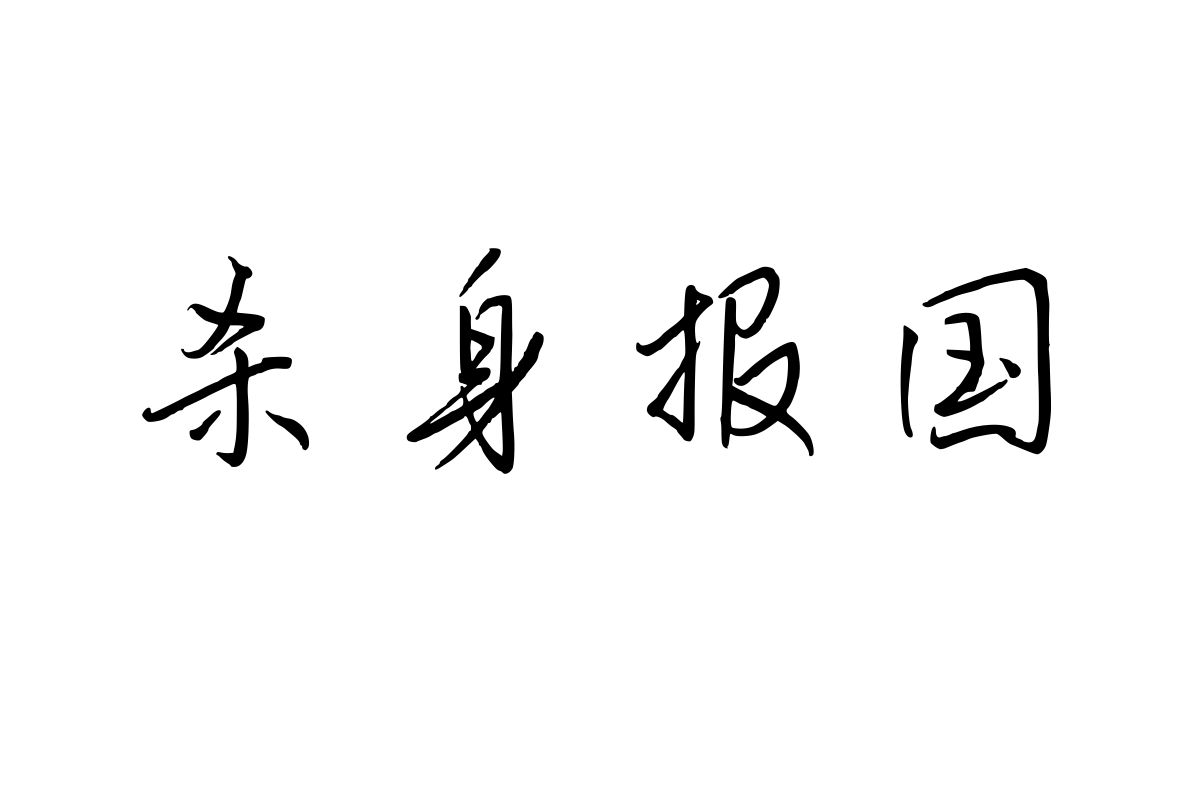
兰米星空物语是一款具有独特设计和艺术风格的字体。这款字体采用了现代和抽象的设计风格,将传统与创新相结合。它的字母形状独特,线条流畅,给人一种优雅而富有艺术感的感觉。
兰米星空物语的特点在于其独特的艺术风格和设计元素。这款字体的字母形状呈现出一种抽象的美感,线条流畅且富有弹性。同时,它还融合了一些现代元素,使得整体视觉效果更加时尚和前卫。
兰米星空物语适用于各种场景,如广告、海报、网站等。它能够很好地传达出品牌的独特性和创意性,吸引观众的注意力。无论是商业广告还是个人项目,兰米星空物语都能够为您带来出色的视觉效果。